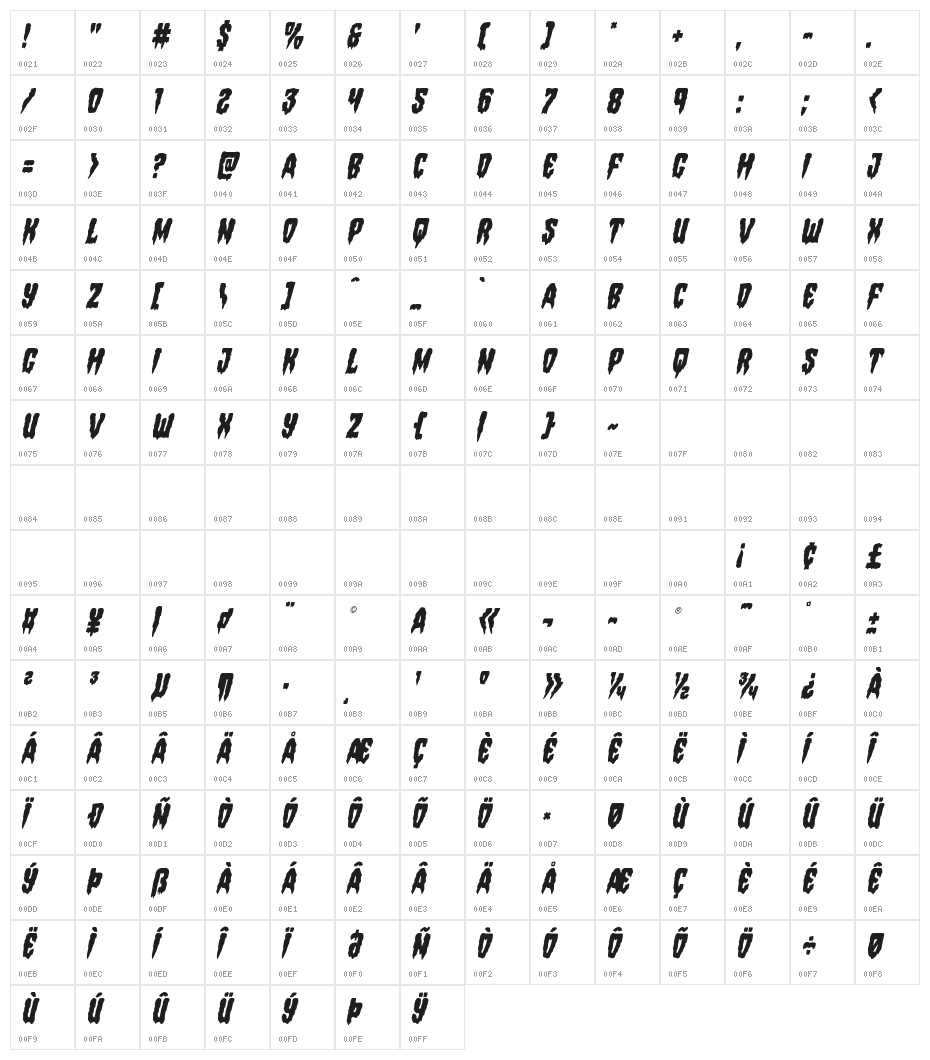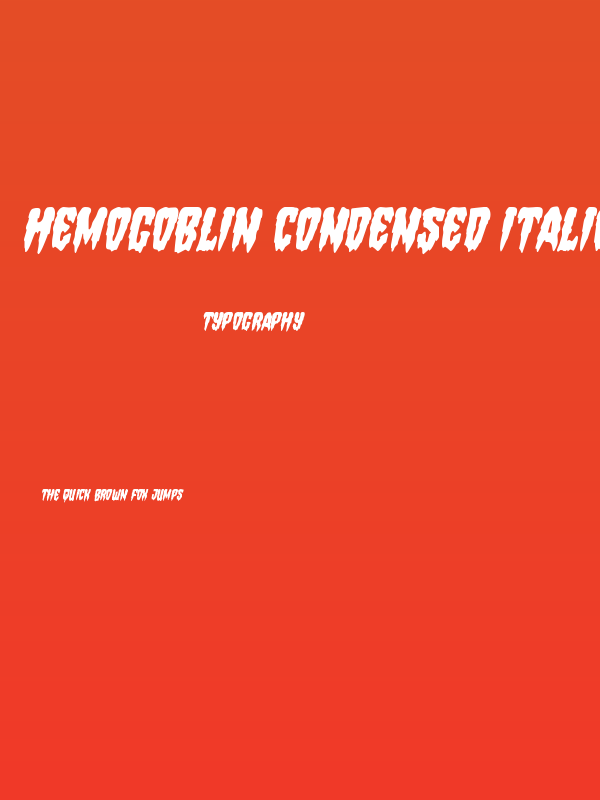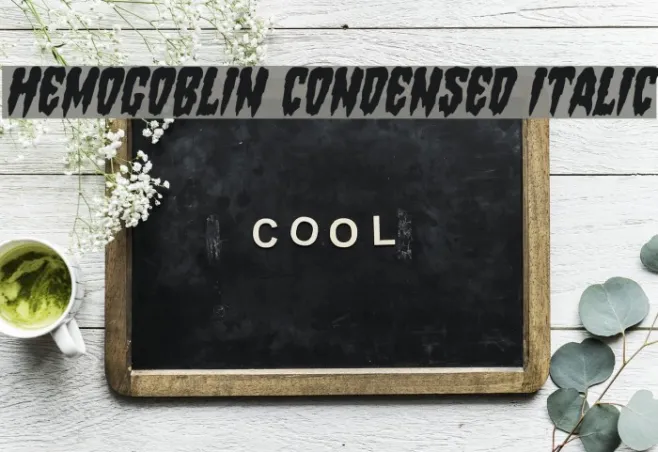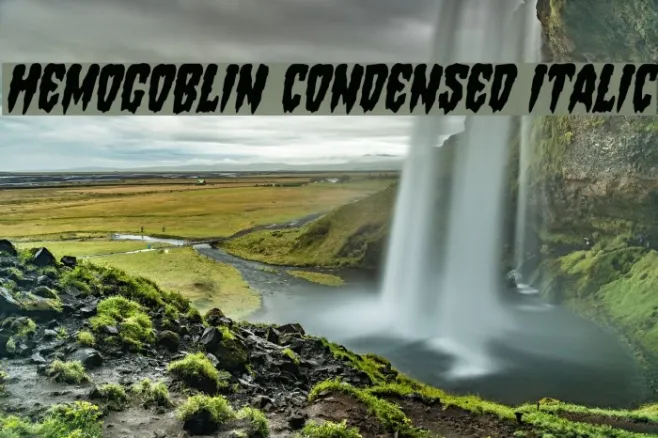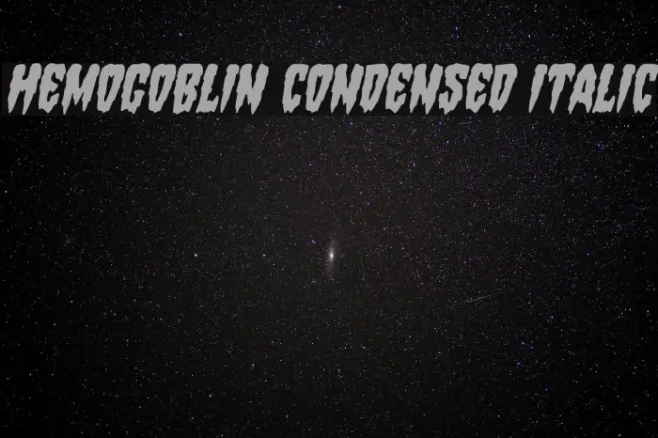
Hemogoblin Condensed Italic Font
| Vorgeschlagene Projekte | Ideal for horror-themed posters, edgy branding, album covers, and video game graphics. |